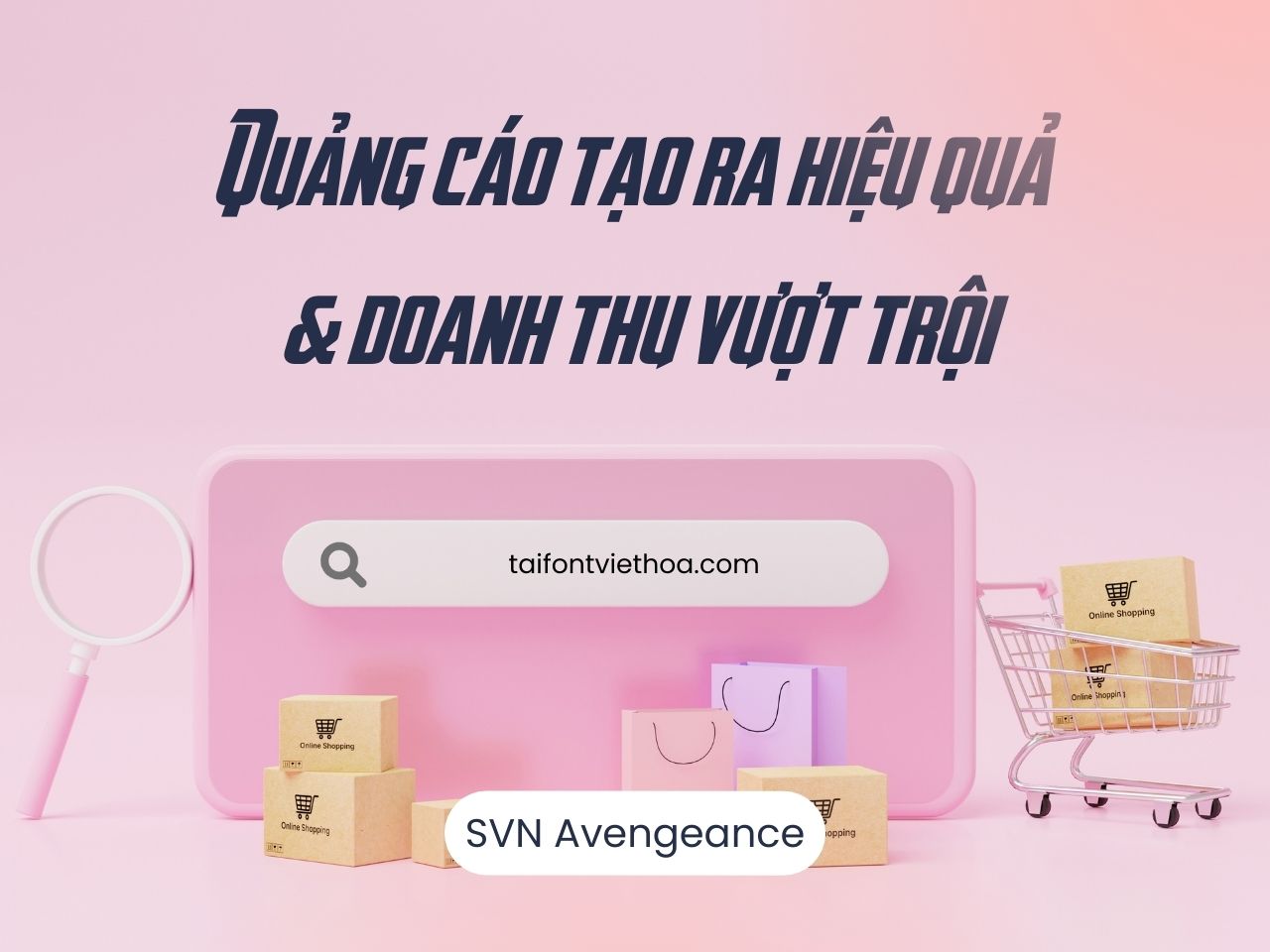
Giới thiệu về font SVN Avengeance – Kiểu chữ sans-serif đậm nét, mạnh mẽ và cá tính
SVN Avengeance là phiên bản Việt hóa của font Avengeance – một kiểu chữ sans-serif mang phong cách đậm nét, mạnh mẽ và rất cá tính. Font được thiết kế với các nét chữ sắc nét, góc cạnh và chắc chắn, phù hợp cho các dự án thiết kế thương hiệu, quảng cáo và truyền thông kỹ thuật số.
Phiên bản Việt hóa của SVN Avengeance đã được Taifontviethoa.comchăm sóc kỹ lưỡng, hỗ trợ đầy đủ dấu tiếng Việt cùng hơn 70 ngôn ngữ khác. Font giúp các nhà thiết kế dễ dàng áp dụng trong nhiều dự án đa dạng mà vẫn giữ được phong cách mạnh mẽ, trẻ trung và chuyên nghiệp.
Thiết kế sans-serif đậm nét – Ứng dụng đa dạng trong thương hiệu và quảng cáo
SVN Avengeance sở hữu các nét chữ dày, rõ ràng và sắc nét, tạo cảm giác nổi bật và thu hút. Font phù hợp sử dụng cho tiêu đề, banner, logo hoặc poster cần sự ấn tượng và cá tính mạnh mẽ. Phong cách thiết kế của Avengeance rất thích hợp với các dự án công nghệ, thể thao, quảng cáo và thương hiệu trẻ trung, năng động.
Ứng dụng lý tưởng: thiết kế logo, poster quảng cáo, banner sự kiện, nhận diện thương hiệu thể thao, website công nghệ và các dự án marketing sáng tạo. Ngành nghề phù hợp: công nghệ, thể thao, giải trí, quảng cáo, thương mại điện tử và startup sáng tạo.